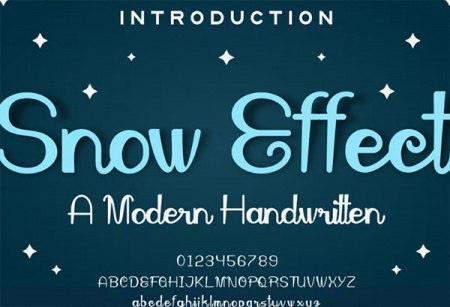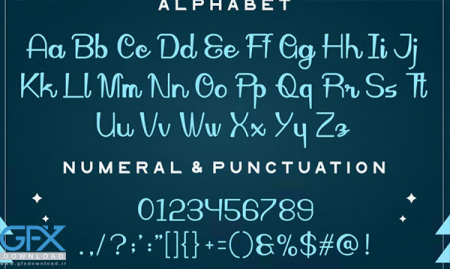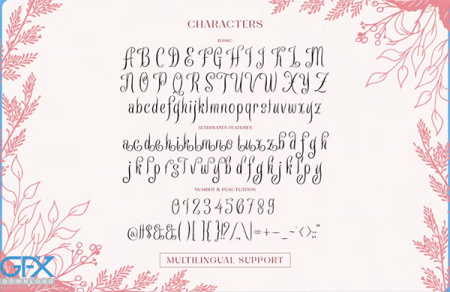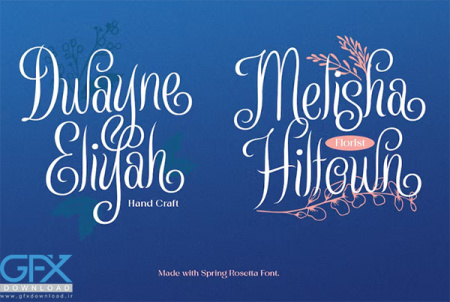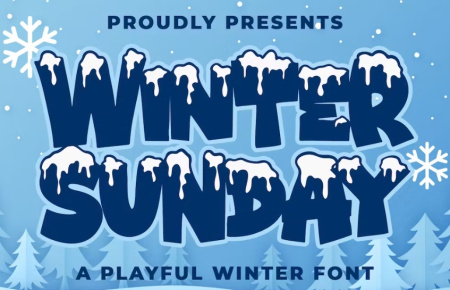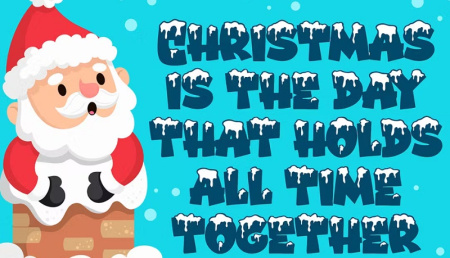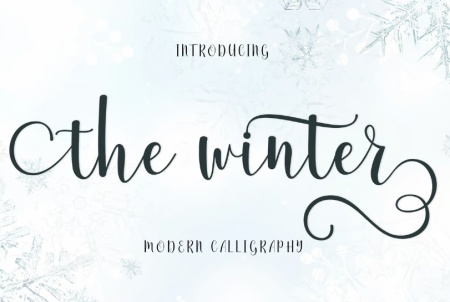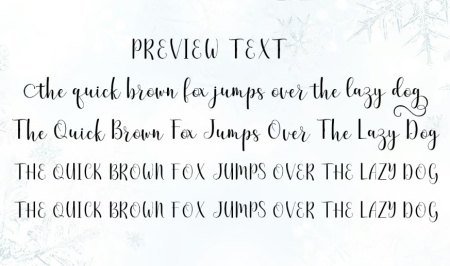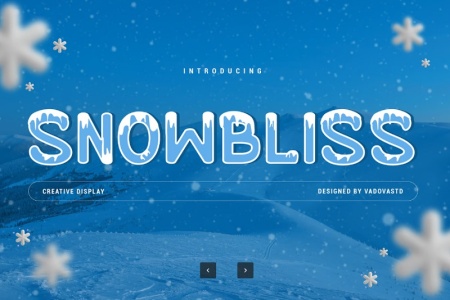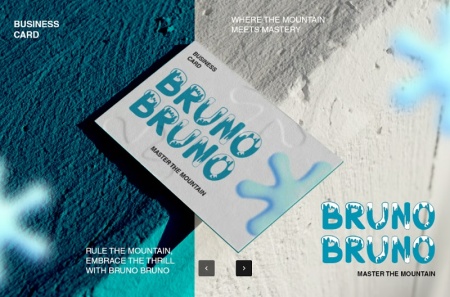
فونت زمستان☃️دانلود 6 فونت انگلیسی زمستانی جدید
فونت انگلیسی زمستان Winter Rosetta
1- دانلود فونت انگلیسی زمستان Winter Rosetta
Winter Rosetta یک فونت انگلیسی اسکریپت زیبا با سبک دست نوشته معتبر و امضا با تم زمستانی و سرد است. این فونت زمستانی با گل / گیاه شناسی که با دست کشیده وکتور ارائه می شود. دانلود رایگان فونت زمستان Winter Rosetta در طراحی لوگو و سایر اشکال رسمی مختلف مانند دعوت نامه، برچسب، لوگو، مجلات، کتاب، کارت تبریک/عروسی، بسته بندی، مد، آرایش، لوازم التحریر، رمان، برچسب یا هر چیز دیگری مورد استفاده است.
فونت زمستانی Snow Effect
فونت زمستانی انگلیسی
2- دانلود فونت زمستانی انگلیسی
اگر به دنبال یک فونت زمستانی و کریسمسی هستید، این فونت زمستان انگلیسی با نام Winter Sunday را به شما پیشنهاد می کنیم. مناسب برای تم زمستانی، کریسمس، جلد کتاب، کتاب کودکان، کمیک، پوستر، بسته بندی، کالا، لوگوتایپ و موارد دیگر می باشد.
فونت انگلیسی زمستانی و فصل سرما
3- دانلود فونت انگلیسی زمستانی و فصل سرما
فونت انگلیسی زمستانی The Winter یکی دیگر از فونت های زمستانی است که حس و حال فصل زمستان و سرما را تداعی می‌کند. این فونت‌ برای طراحی پوسترهای کریسمس، کارت‌های تبریک زمستانی، بنرهای فروش ویژه زمستانی و هر نوع طراحی دیگری که به فصل زمستان مرتبط باشد مناسب است.
فونت زمستان و برفی انگلیسی
4- دانلود فونت زمستان و برفی انگلیسی
فونت زمستان و یخی انگلیسی برای طراحی گرافیکی
مجموعه فونت زمستان و یخی انگلیسی برای طراحی گرافیکی
اگر به دنبال یک فونت زمستون انگلیسی برای طراحی پوستر، بنر یا پروژه‌ های گرافیکی فصلی هستید، فونت‌ های زمستانی و یخی می‌ توانند بهترین انتخاب باشند. این نوع فونت‌ ها با الهام از برف، یخ و حس سرد زمستان طراحی شده‌ اند و جلوه‌ ای خاص و چشم‌ نواز به طرح‌ های شما می‌ دهند. با دانلود فونت زمستان و یخی می‌ توانید در طراحی کاور شبکه‌ های اجتماعی، پوستر های تبلیغاتی، کارت تبریک سال نو، طراحی لوگو و حتی پروژه‌ های دیجیتال آرت، فضایی سرد و حرفه‌ ای ایجاد کنید.
✅ نام فونت شماره یک: Winter Rosetta
✅ نام فونت شماره دو: Snow Effect
✅ نام فونت شماره سه: Winter Sunday
✅ نام فونت شماره چهار: The Winter
✅ نام فونت شماره پنج: Snowbliss Creative
✅ نام فونت شماره شش: Estave - Winter
✅ حروف بزرگ و کوچک
✅ اعداد و علائم نگارشی
✅ چند زبانه
✅ متناوب و لیگاتورها
فونت انگلیسی زمستانی با نام Snow Effect